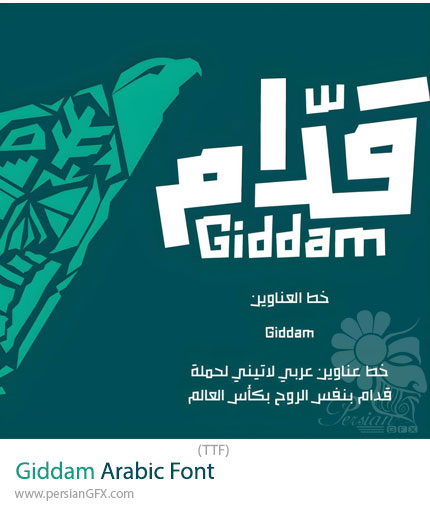
در این بخش شاهد فونت عربی قدام می باشید که با فرمت TTF بر روی سایت برای دانلود قرار گرفته است. Giddam Arabic Font یک فونت عربی زیبا و حرفهای با طراحی مدرن است که برای ایجاد طرحهای گرافیکی چشمگیر، پروژههای برندینگ، پوستر، لوگو و محتوای دیجیتال طراحی شده است. این فونت با ترکیب فرمهای سنتی حروف عربی و سبکهای تایپوگرافی معاصر، ظاهری خاص و منحصربهفرد به نوشتهها میبخشد. ساختار نرم، منحنیهای هماهنگ و شخصیت بصری جذاب Giddam باعث شده این فونت برای طراحیهای لوکس، فرهنگی، تبلیغاتی و پروژههایی که نیاز به حس اصالت و زیبایی دارند، انتخابی مناسب باشد. Giddam Arabic Font یک فونت عربی زیبا و کاربردی برای طراحانی است که به دنبال ایجاد نوشتههایی متفاوت، حرفهای و چشمگیر هستند. این فونت با ظاهر مدرن و شخصیت بصری خاص، گزینهای مناسب برای لوگو، پوستر، تبلیغات، شبکههای اجتماعی و پروژههای خلاقانه گرافیکی است.
ویژگیهای کلیدی:
✔ فونت عربی با طراحی مدرن و چشمنواز
✔ مناسب برای تایپوگرافی و طراحی گرافیک
✔ دارای فرمهای نرم و خوانایی بالا
✔ مناسب برای تیترها و نوشتههای بزرگ
✔ ایجاد حس لوکس و هنری در طراحیها
✔ قابل استفاده در پروژههای چاپی و دیجیتال
✔ مناسب برای طراحی برند و هویت بصری